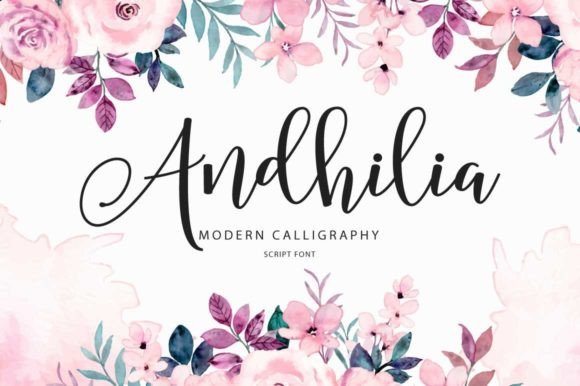
Andhilia
適切なデザイン要素を見つけるのは難しい場合がありますが、Andhiliaは作品を即座に引き立てる優れたコレクションを提供します。
精密に作られたAndhiliaは、クリーンなベクター、滑らかなタイポグラフィ、そして安心のための商用ライセンスを提供します。
POD(オンデマンド印刷)製品、結婚式の招待状、またはソーシャルメディアのグラフィックを作成している場合でも、Andhiliaは理想的です。